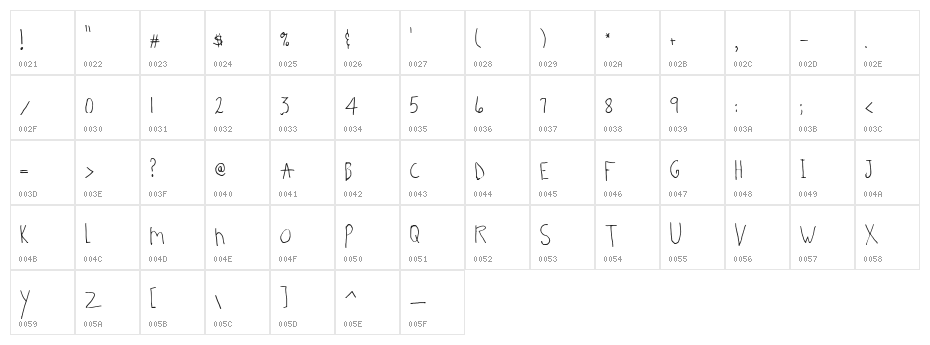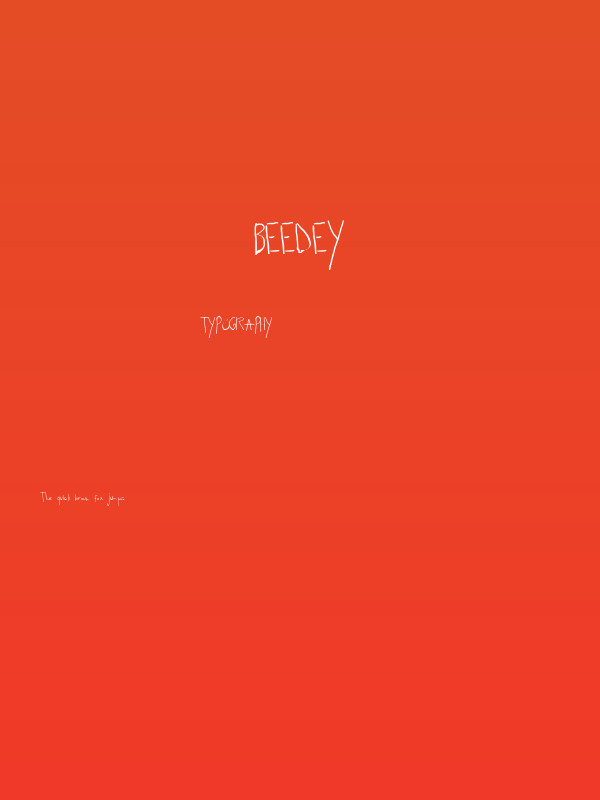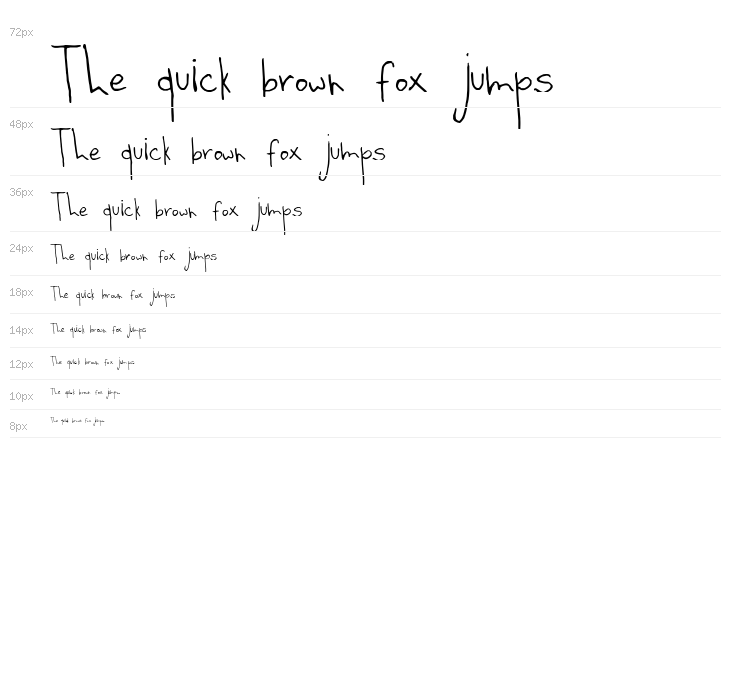
Beedey Font
| Gesamtstil | Casual, Playful |
| Anwendungsfall | Headlines, Informal text, Creative projects |
| Vorgeschlagene Projekte | Ideal for greeting cards, children's books, personal blogs, and informal branding. |